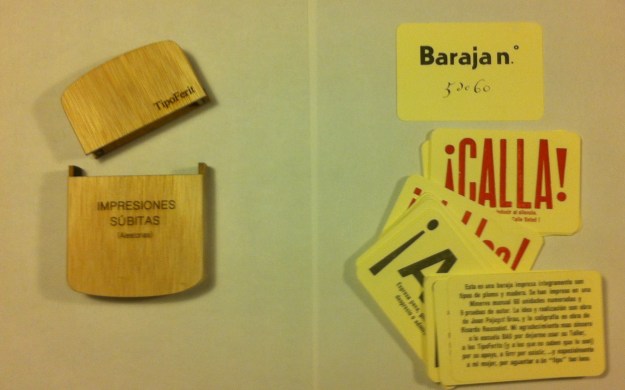
Os presento mi nuevo proyecto “Impresiones Súbitas aleatorias” terminado a finales de Junio. Es este un proyecto que me ha llevado dos años de trabajo y algunos quebraderos de cabeza. (Cuando digo dos años no son a tiempo completo claro, si no a los ratos que podía sacar a mi casa y mi familia…después de mi trabajo “normal”)
La idea surgió mientras leía un viejo libro de enseñanza de la Tipografía de la Escuela Virgen de la Paloma de Madrid. (actualmente tengo entendido IES de Formación Profesional). En este libro maravilloso no solo se enseñaban las formas de preparar las tintas, los moldes, las encuadernaciones, etc,etc. Enseñaban gramática, que como todo el mundo sabe es muy útil a los impresores. Como iba diciendo, mientras repasaba la parte gramatical del libro, mis ojos se posaron en la definición de Interjección: Del latín “Interectio, Interiectionis”. Voz que formando por si sola una oración elíptica o abreviada, expresa una impresión súbita como asombro, dolor, molestia, amor, etc. Aquellas dos palabras, “impresión súbita” en medio del texto me resaltaron como si estuvieran impresas en rojo. Impresión súbita, impresión tipográfica…
Tenía que fabricar alguna cosa impresa uniendo las dos cosas.
Primero pensé en unas hojas en las que imprimiría las interjecciones y se me ocurrió una encuadernación en acordeón como las de las antiguas postales, el problema era que tenía que hacer 43 interjecciones y aún usando las dos caras de la hoja mas hojas explicativas etc. me salían un mínimo de 23 hojas tamaño aprox 9 x 6 cms. unidas, igual a 138 cms. de largo, además el grueso contando un papel de 120 gr mínimo mas los dobleces sería un paquete incomodo para guardar. Efectué una maqueta a tamaño tarjeta de crédito (8,5 x 5,5 cms.) y me di cuenta primero de la complejidad de la encuadernación, y luego de que los bordes del paquete molestaban mucho. Así que le hice unos cantos romos a las 4 esquinas…al momento caí en la cuenta, parecía una baraja de cartas.
Dicho y hecho convertí mi primera idea en una baraja, y enseguida pensé en usar la Superveloz para el dorso de las cartas. Además si tenía una baraja de interjecciones, la podía mezclar y…¡Zas! me saldría una interjección aleatoria.
Impresiones Súbitas (Aleatorias)
¡Que bonito titulo!
Luego resultó que recibí apoyo moral de mis amigos Tipoferits…(a ver si lo acabas tío que llevas 2 años ya!!), que resultó también que el proyecto gustó al “Calígrafo” y “Pendolista” Ricardo Rousselot, y que a los amigos de Arteina les pareció mejor una primorosa caja de madera que la clásica fournier de cartón que era mi primera idea. Así que…aquí tenéis el resultado, 60 unidades más nueve pruebas de autor de las “Impresiones Súbitas aleatorias”
Y esta, señoras y señores, niñas y niños, extraterrestres varios que me leéis es la manera sutil (pero complicada) en que se pasa de ojear/leer un libro a crear un proyecto tipográfico resultón.
(Aviso que es mucho más impactante en vivo que en fotos)